In der Fachsprache von Kommunikationsagenturen und Verlagen bzw. im Fachjargon von Journalisten:innen, Texter:innen sowie Public Relations- und Werbeabteilungen von Unternehmen und Organisationen ist »Copy« ein Fachbegriff für den »Fließtext« eines werblichen Schriftsatzes, bspw. im Rahmen einer Presse-, PR- oder Unternehmensmitteilung; Fließtext eines Werbetextes, z.B. innerhalb einer werblichen Publikation; Copytext; Anzeigentext; ggf. Fließ-, Haupt- bzw. Mengentext eines redaktionellen Beitrags; Pl. »Copies«
Struktur
Die Copy (Fließtext) steht hierarchisch unter der Headline (Überschrift) und der Subline (Unterzeile). Eine Copy kann mit Zwischenüberschriften (Subheading) gegliedert werden.
Hierarchie von Headline, Subline und Copy:
1. Headline (Überschrift)
2. Subline (Unterzeile der Überschrift)
Copy (Fließtext)
Hierarchie von Headline, Subline, Dateline, Subheading und Copy:
1. Headline (Überschrift)
2. Subline (Unterzeile der Überschrift)
Dateline (Spitzmarke)
Copy (Fließtext)
( ... )
Copy (Fließtext)
3. Subheading (Zwischenüberschrift) 1)
Copy (Fließtext)
In der Typografie besteht die Copy aus einem Fließtext, der i.d.R. in der Grundschrift und in einer Lesegröße gesetzt ist.
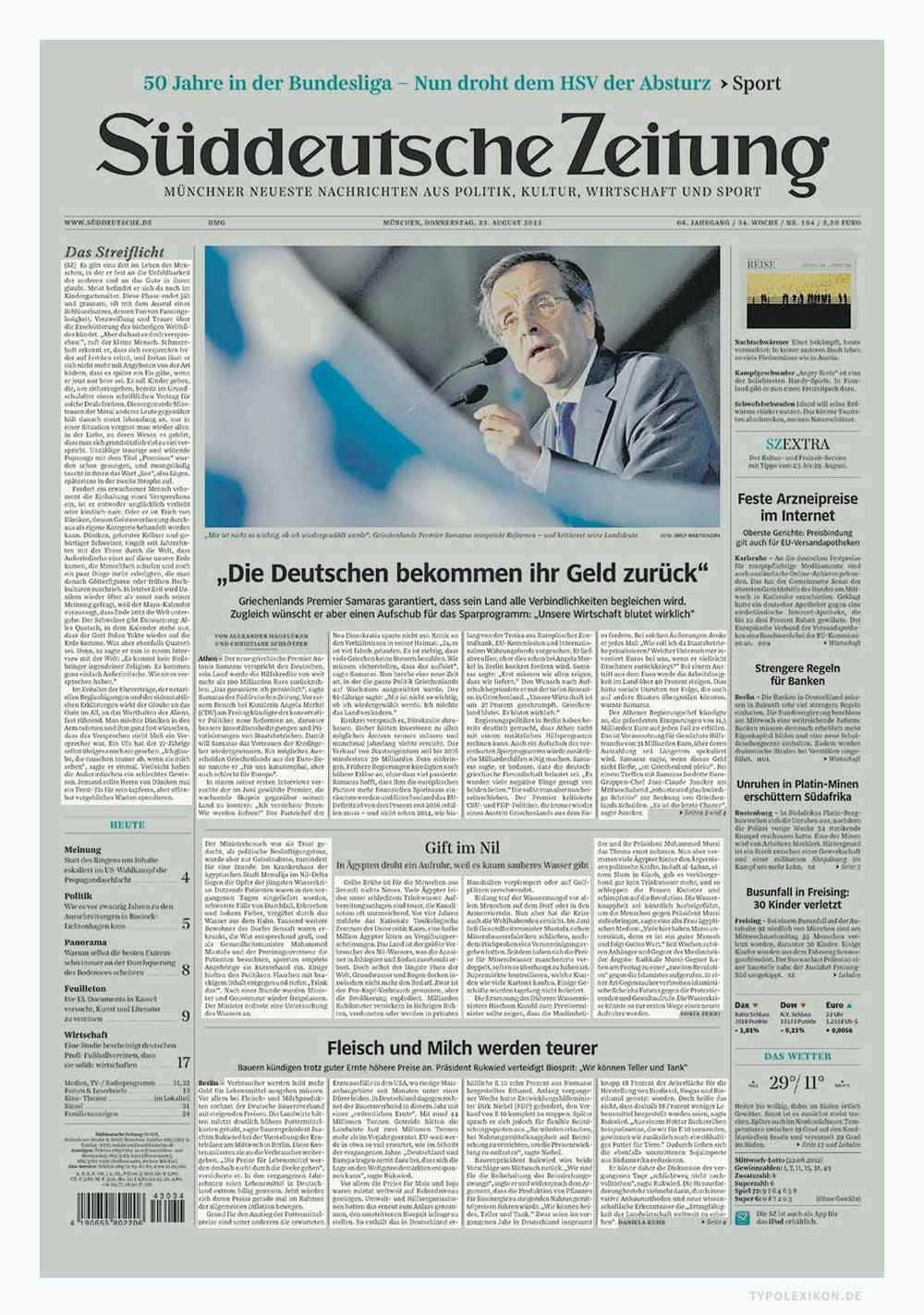
Die Schriftwahl für die Copy gehört in das Segment der Makrotypografie. Fließtexte zählen zur Integralen Schriftmischung und werden deshalb in einer semantisch-typografischen Auszeichnungsmatrix gegliedert und dokumentiert.
Etymologie und Herkunft
Etymologisch von eng. »copy« für »Kopie, Abschrift, Nachbildung, Durchschlag, Muster« zu »(Text)Abdruck«.
Ab den 1920er Jahren wurde der Begriff Copy in den USA – insbesondere von der neuen Berufsgruppe der »Type Directors«, die in den neu gegründeten »Advertising Service Agencies« (Full Service Werbeagenturen) die Akzidenzsetzer verdrängten und später zu »Art Directors« wurden – aus dem Fachvokabular der Zeitungstypografie adaptiert.
Im deutschsprachigen Raum taucht der Anglizismus für Unterzeile in Anzeigen, Werbekatalogen und Werbeprospekten dann vermutlich erstmals in den 1950er Jahren mit den ersten deutschen Dependancen US-amerikanischer Werbeagenturen, z.B. McCann Erickson und J. Walter Thompson, im Frankfurter Raum (Hessen) auf.
Mit dem deutschen Wirtschaftswunder ab den 1950er Jahren und der damit verbundenen Prosperität des Wirtschaftsclusters »Kultur- und Kreativwirtschaft«, wurde der Anglizismus ab den 1970er Jahren sukzessive – so wie andere Anglizismen auch, bspw. die Begriffe Headline, Subline und Layout – in Westdeutschland (BRD), Österreich und der deutschsprachigen Schweiz in die gängige Werbesprache bzw. in den gewebsspezifischen Sprachschatz übernommen.
Von diesem Wortstamm leiten sich u.a. folgende Fachbezeichnungen ab:
- Copy chief = Cheftexter
- Copy deadline = Redaktionsschluss
- Copy department = Textabteilung
- Copy platform = Fundament für eine Textaussage, Gestaltungsgrundlage
- Copy resarch = Textanalyse
- Copyright = Urheberrecht, Urheberschutz, Eigentumsrecht
- Copy test = Verfahren der Umfrageforschung, bei dem anhand der Copy festgestellt wird, was der Befrage gesehen, gelesen, wiedererkannt oder behalten hat
- Copy writer = Werbetexter